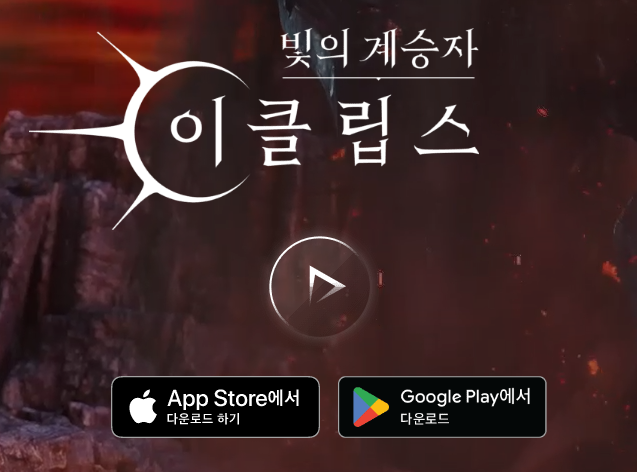
판타지 수집형 RPG 게임인 빛의 계승자 이클립스에서 제공하는 일명 계승자체라 불리는 글꼴인 빛의 계승자 폰트를 무료로 다운로드하는 방법을 살펴본다. 더불어 누구나 무료로 사용이 가능한 빛의 계승자 폰트를 윈도우에 설치하는 방법을 소개한다.
누구나 개인적인 용도뿐만 아니라 상업적인 용도에도 무료로 사용할 수 있도록 제공하는 무료 글꼴인 빛의 계승자 폰트를 소개한다. 빛의 계승자 폰트는 게임 속에 등장하는 독특하면서도 섬세한 장식적인 요소가 매력적인데 한글뿐만 다양한 언어 출력이 가능한 다국어 글립도 제공하고 있다. 다음에서 제시하는 순서대로 따라 하면 빛의 계승자 폰트 폰트를 무료로 다운로드해서 사용할 수 있다.
빛의 계승자 폰트는 빛의 계승자 이클립스 게임을 개발한 모바일 게임 스튜디오 펀플로와 산돌구름이 콜라보 프로젝트로 제작해서, 빛의 계승자 이클립스 게임 홈페이지에서 무료로 제공하고 있다.
위의 이미지에서 보듯이 빛의 계승자 폰트는 날카로운 세리프와 화려하고 고풍스러운 그래픽을 장식적인 디자인 요소로 표현함으로써, 빛의 계승자 이클립스 게임의 세계관인 다크 판타지 컨셉에 매치하도록 어둡고 진중한 분위기를 전달하고 있다.
위에서 보듯이 빛의 계승자 폰트는 레굴러를 기본으로 강조한 볼드체 2종으로 구성되는데, 글꼴의 세로와 가로 부분을 보면 가늘고 뾰족한 형태를 볼 수 있다. 마치 펜톡으로 쓴 듯 부리 형태로 톡 튀어나온 형상을 지니고 있어서, 앞에서 언급했듯이 장식적인 요소가 도드라지는 서체이다. 이러한 빛의 계승자 폰트를 컴퓨터에 설치하는 방법은 매우 간단하다. 설치를 원하는 해당 파일을 누른 후에 나오는 팝업에서 설치 버튼을 눌러주면 된다.